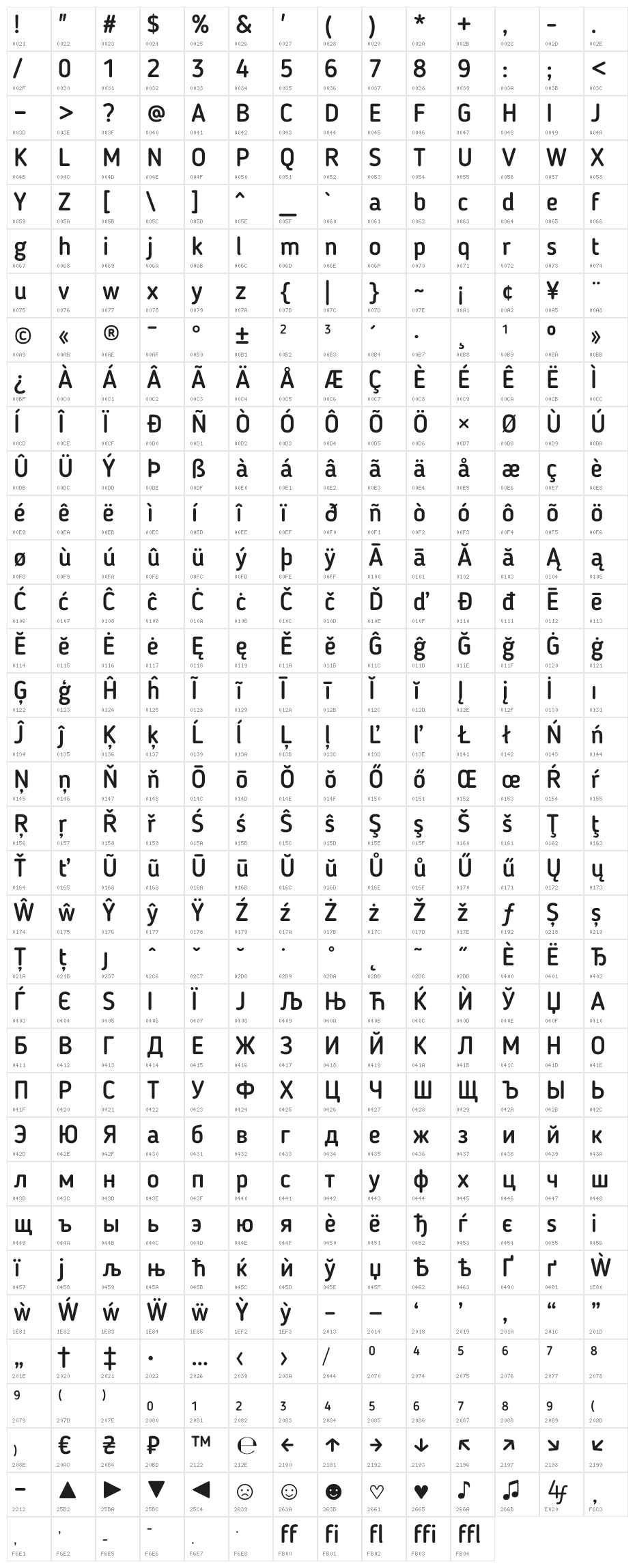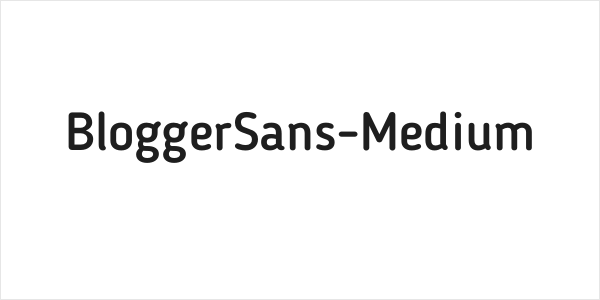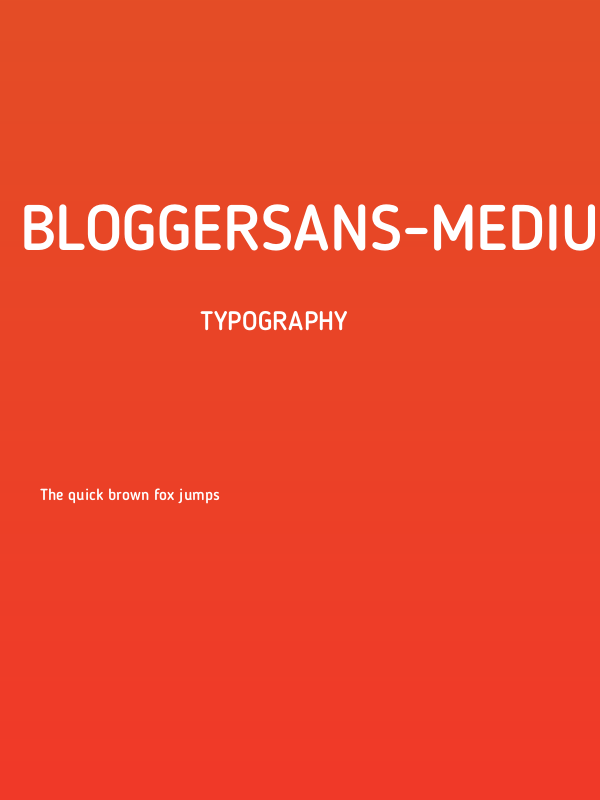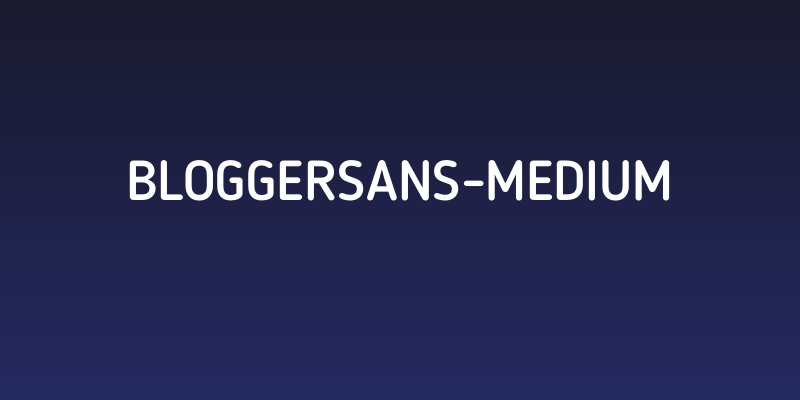
BloggerSans-Medium Font
Diese Schriftart enthält 545 Zeichen. Klicken Sie auf ein Zeichen für Details.
| Anwendungsfall | Headlines, Body text, Logos |
| Vorgeschlagene Projekte | Ideal for web design, branding, user interfaces, and print materials where a modern and friendly look is desired. |